Awal Mula Meme Font DOM JATIM Viral dan Cara Pakainya
Baru-baru ini, media sosial X (Twitter) mendadak ramai dengan meme atau template komentar DOMISILI MANA dan JAUH AKU JATIM. Semakin unik, meme ini menggunakan gaya font yang tak biasa.
1. Meme font DOM JATIM berasal dari tangkapan layar percakapan salah seorang netizen di DM
Meme viral ini berawal dari unggahan akun @mybabyIAN_ atau Anny di X. Ia menunjukkan tangkapan layar percakapannya dengan seseorang di DM. Tampak sedang dalam tahap saling kenal, Anny kemudian ditanyai soal domisilinya.
Namun, netizen salah fokus dengan font dari sang pengirim DM. Bukan font default dari ponsel, melainkan gaya tulisannya jauh lebih besar, dengan capslock, dan tampak bergaya.
2. Cara pakai font 'DOM JATIM'
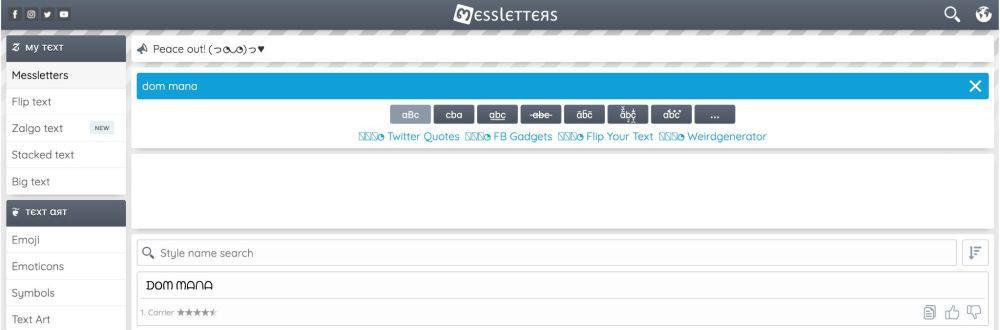
Netizen lalu kompak menyebut jenis tulisan tersebut sebagai 'font dom Jatim'. Padahal sebenarnya, font itu Banyak yang ingin ikut menulis dengan tipografi tersebut tanpa mengunduh aplikasi apapun.
Kalau kamu salah satunya, berikut cara untuk menggunakan font dom Jatim.
- Buka https://www.messletters.com/en/
- Ketik teks yang diinginkan
- Pilih hasil teks dari font 'Carrier'
3. Jadi meme viral di kalangan netizen
Tipografi font tak biasa ini menjadi semakin ramai diperbincangkan setelah akun @irzanhakim alias Irzan melakukan voice over untuk percakapan tersebut.
Bahkan, beberapa selebgram juga mulai terkena demam font dom Jatim ini. Gak ketinggalan, muncul meme-meme terkait jenis tulisan lucu ini disertai percakapan 'Domisili mana?' dan 'Jauh aku Jatim'.